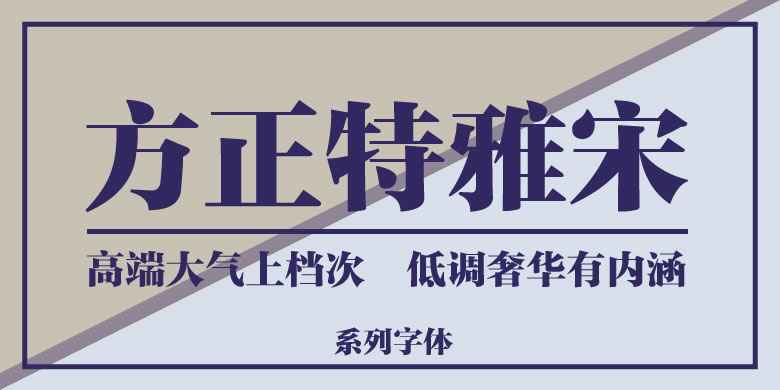
方正雅宋系列
品牌:方正字库设计师:朱志伟发行时间:2007字库编码:大陆简体(GB2312-80)、大陆繁体(GB12345-90)、简繁扩展(GBK)、港台地区(BIG-5)分类:宋体
方正雅宋最初是为丰富标题宋体字而设计。源自铅字时代的宋体字,从字形结构到笔画风格都难以满足日益丰富的应用需求,方正雅宋诞生于全新的数字时代,字形结构饱满,中宫放松,笔形挺拔流畅,笔锋简洁鲜明富有朝气。方正雅宋家族具有9款字重,外加2款窄字身和扁字身的字体,可同时满足标题和正文的排版需求。这款字的整体风格清新醒目、现代时尚,不但适用于各类传统纸媒,因其横竖笔画粗细适度,还可直接用于屏幕阅读。